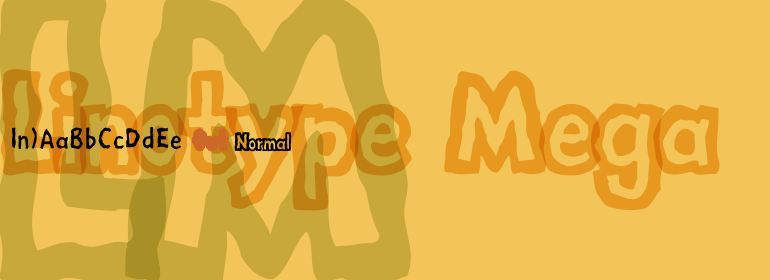
Linotype Mega™
Linotype Mega™,这款字体结构工整、笔画清晰,兼顾美观与易读性,适用于标题、正文、海报、包装、LOGO 等多种场景。字形优雅稳定,风格百搭耐看,适配日常排版与创意设计,让文字呈现更舒适、更具质感。Linotype Mega™一笔一画,皆是细节,以均衡的比例、流畅的线条打造舒适视觉体验,字形端正大气,风格简约现代。无论是商业设计、品牌宣传还是日常排版,都能轻松驾驭,让文字更有格调与力量。Linotype Mega™字体下载。
字体品牌: Linotype(Monotype) 设计师:Teenck,Till F. 字体分类:衬线体 字体属性:外文 字符集:Unicode 发布时间: 2018